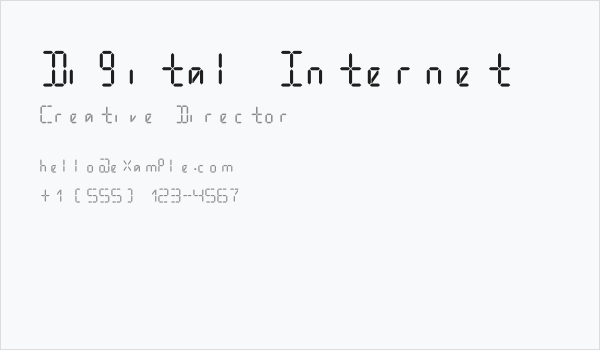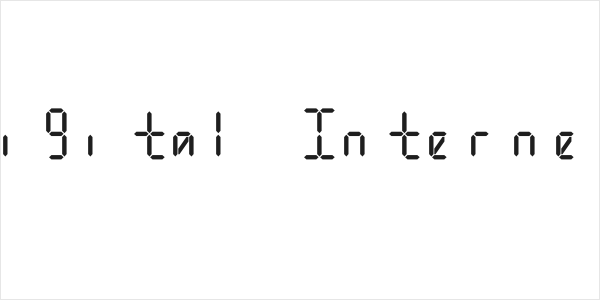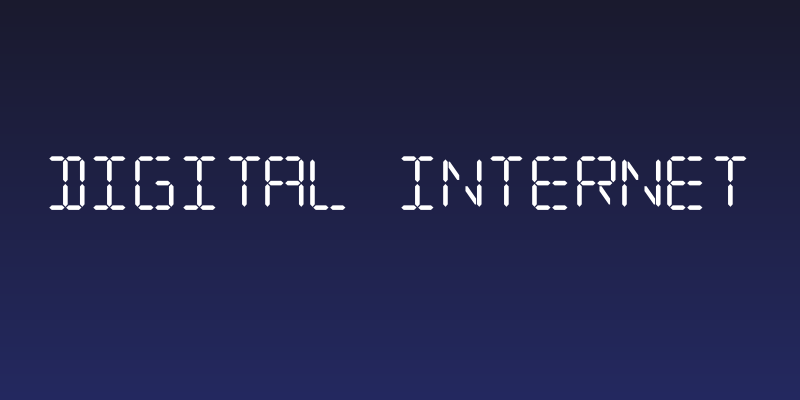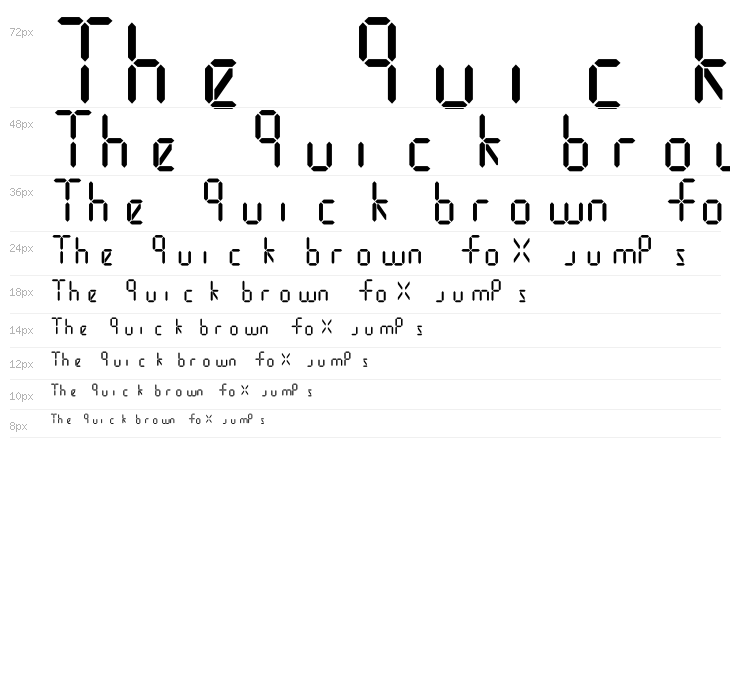
Digital Internet Font
इस फ़ॉन्ट में शामिल हैं 2241 अक्षर। विवरण देखने के लिए किसी भी अक्षर पर क्लिक करें।
DIGITAL-INTERNET अपरकेस
DIGITAL-INTERNET लोअरकेस
DIGITAL-INTERNET अन्य घर का काम
| उपयोग का मामला | Headlines, Logos, Digital displays |
| सुझाए गए प्रोजेक्ट | Ideal for digital interfaces, tech branding, futuristic posters, and electronic device displays. |